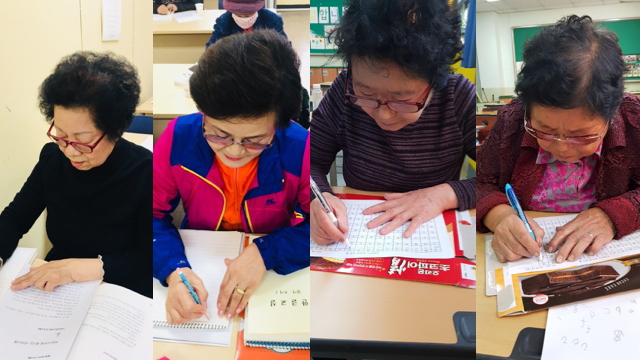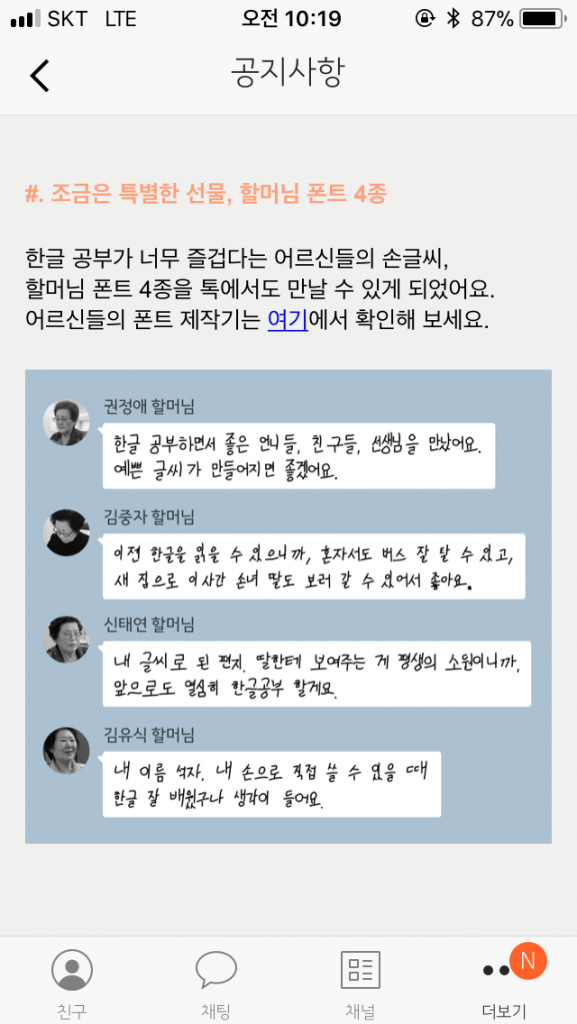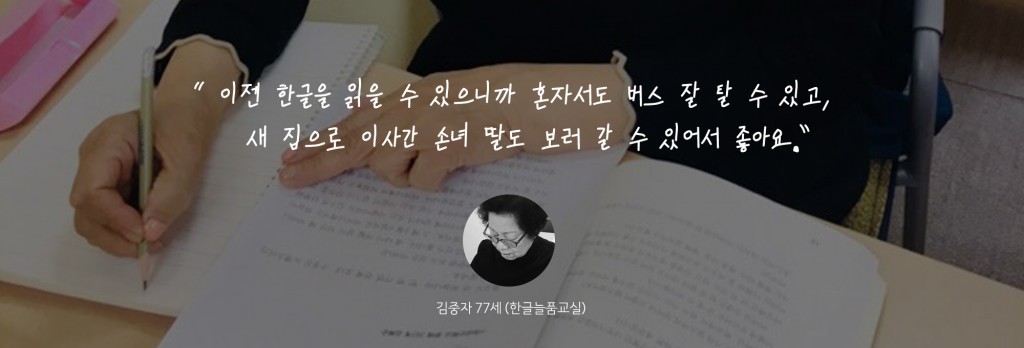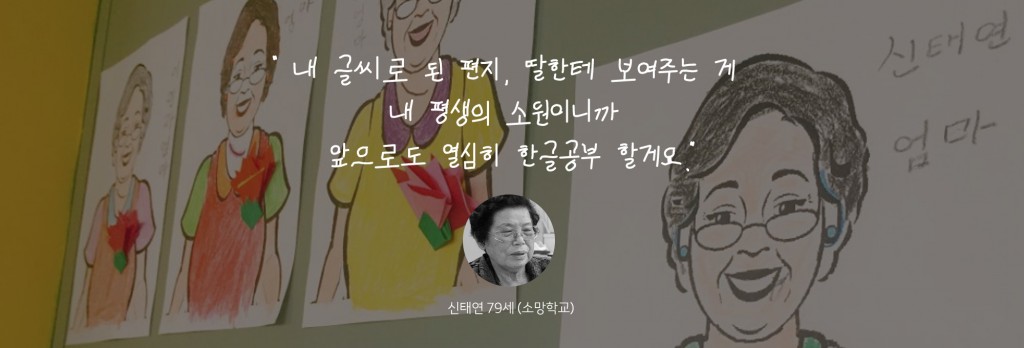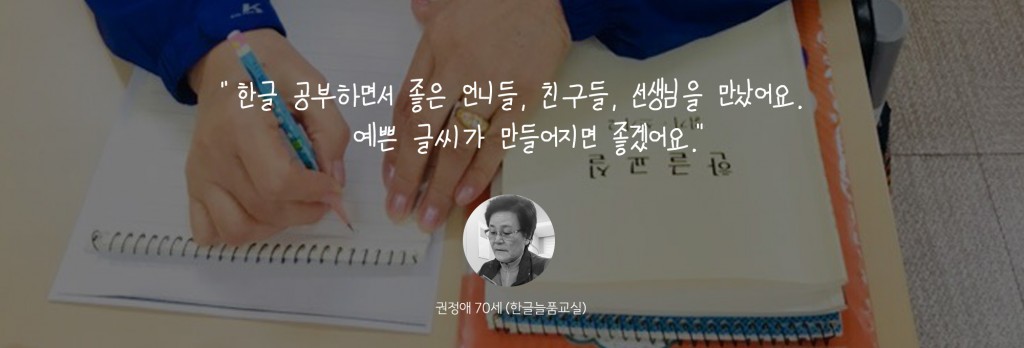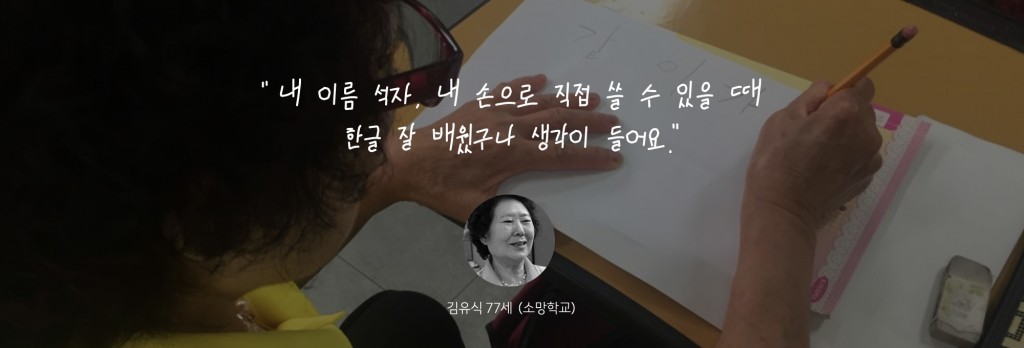
카카오, 할머니들의 정성과 노력 담긴 폰트 4종 무료 배포
지난 14일, 카카오에서 한글을 처음 배운 70대 할머니들의 글씨로 폰트 4종을 무료로 배포했다.
이번에 배포된 폰트는 실제 할머니들의 이름을 딴 ‘권정애체’, ‘김중자체’, ‘신태연체’, ‘김유식체’로 이루어져 있으며, 카카오톡과 PC(윈도우/맥)에서 모두 사용이 가능하다.
‘할머님 폰트’는 카카오의 사회공헌 플랫폼인 ‘같이가치’에서 10주년을 맞이하여 준비한 프로젝트의 일환으로, 어린 시절 못다한 학업의 꿈을 이루기 위해 열심히 한글을 공부하는 할머니들의 손글씨를 폰트로 만들어 배포하면 좋겠다는 취지로 시작되었다.